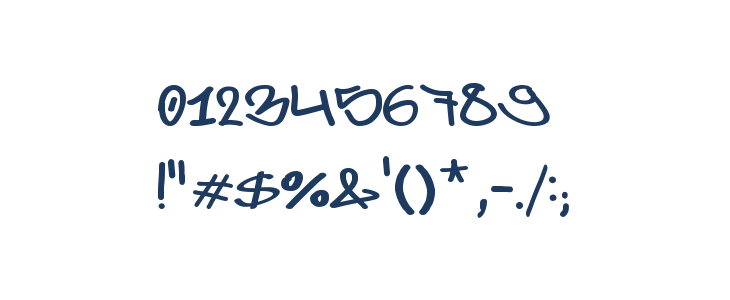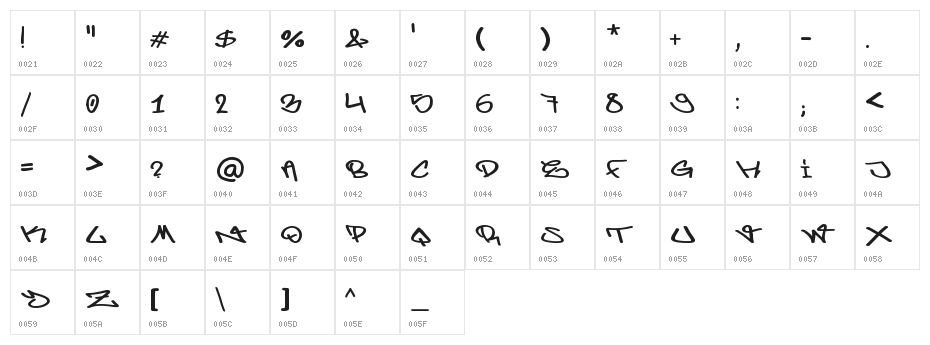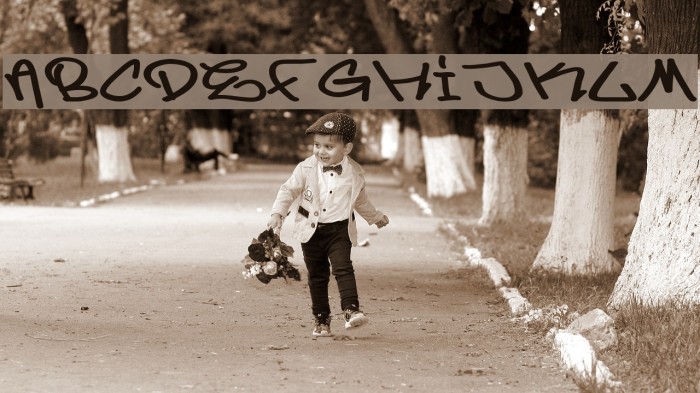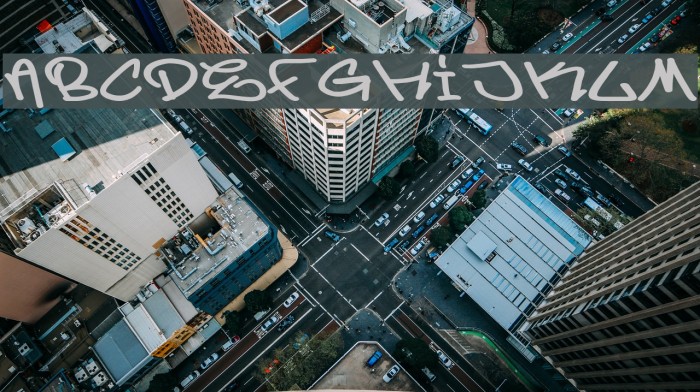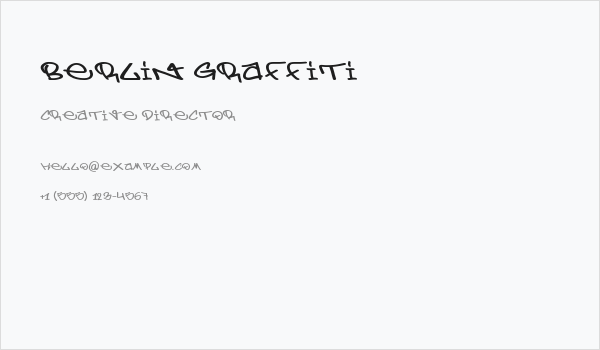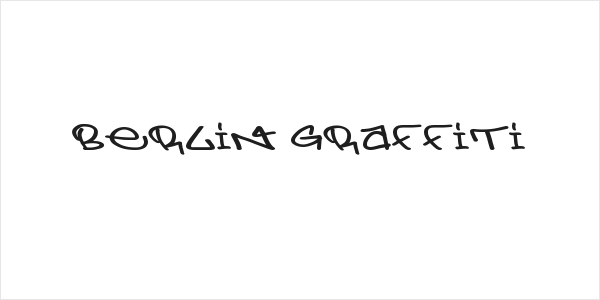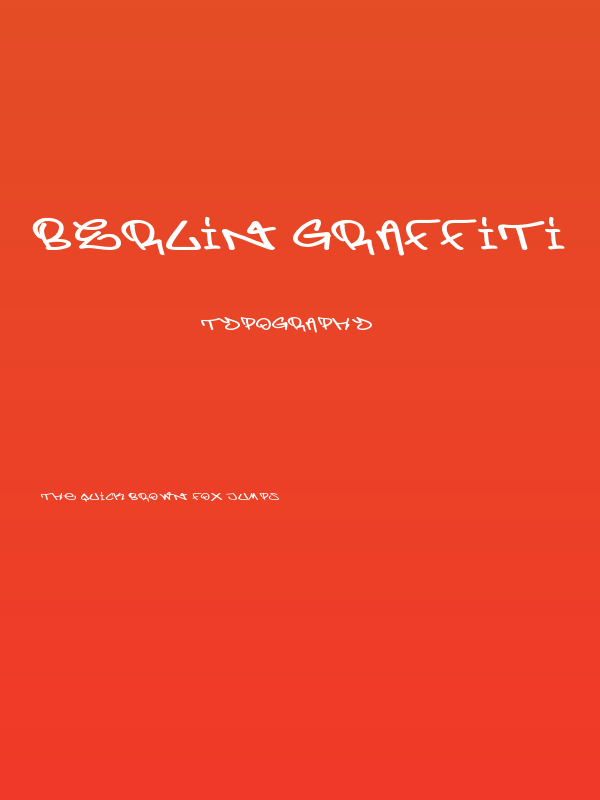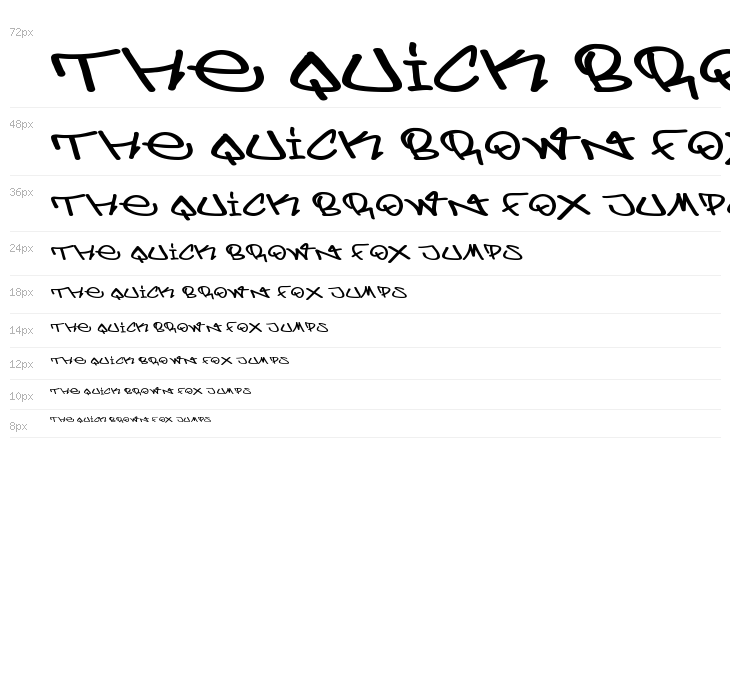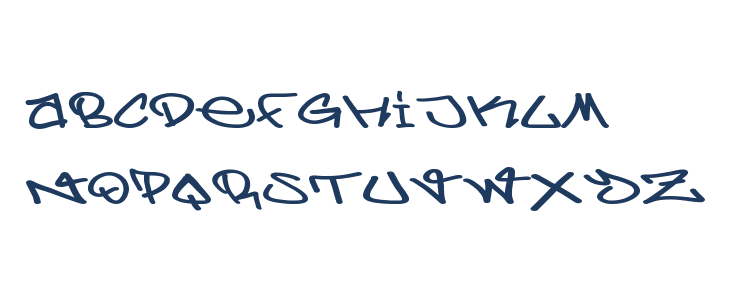
Berlin Graffiti Font
| Kategorien | Graffiti |
| Gesamtstil | Urban, Edgy, Artistic |
| Anwendungsfall | Logos, Headlines, Posters |
| Vorgeschlagene Projekte | Perfect for streetwear branding, music album covers, urban event posters, and creative art projects. |